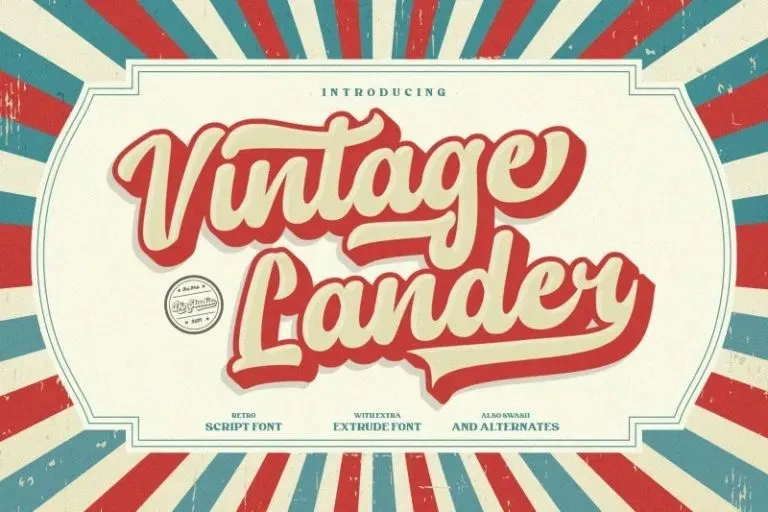
Vintage Lander Font
Esta é uma fonte script vintage bold fabricada pela Din Studio. Com seus traços fortes e tiras grossas, essa fonte é ideal para quando você quer criar aquele visual clássico de fonte bolha. Esta fonte se torna ainda mais especial com a opção de extrusão. Esta fonte pode ser usada em uma ampla gama de necessidades e projetos de conteúdo. Use-a para criar belas citações impressas, pacotes stand out ou t-shirts incríveis! Você até mesmo pode usá-la para criar marcas maravilhosos, logomarcas, menus e gráficos para mídias sociais! Avente esta fonte Vintage Lander Font se você busca algo elegante e versátil. Seja para seu site ou impressão em cartões de visita, suas propostas serão impecáveis. É uma fonte que irá fazer a diferença quando você está buscando um estilo retro moderno. Experimente-a hoje mesmo para ver como ela pode transformar o visual do seu próximo projeto!